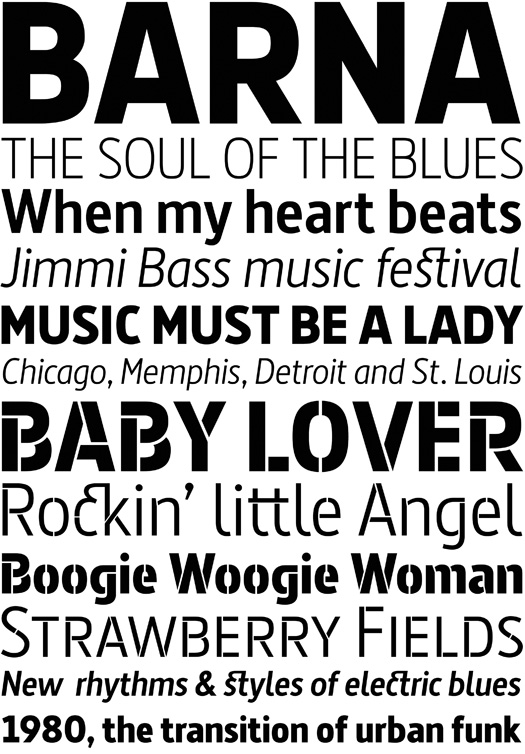
Acaba de salir del horno de Typerepublic, BARNA, una excelente tipografía consistente en una profunda revisión y ampliación de su anterior Dsignes. Según nos cuenta está diseñada para su uso en cuerpo de texto de lectura y su aspecto simple y racional la hace especialmente útil para la composición de textos de carácter técnico.
La familia Barna incluye una ámplia gama de variantes: light, regular, semi-bold, bold, black y sus correspondientes variantes cursivas. Incluye, además, una versión estarcida, «Barna stencil» que aporta un carácter más urbano al conjunto.
Barna dispone de un set completo de caracteres y glifos, incluyendo versalitas, ligaduras, numerales alineados, elzevirianos, tabulares y otros.